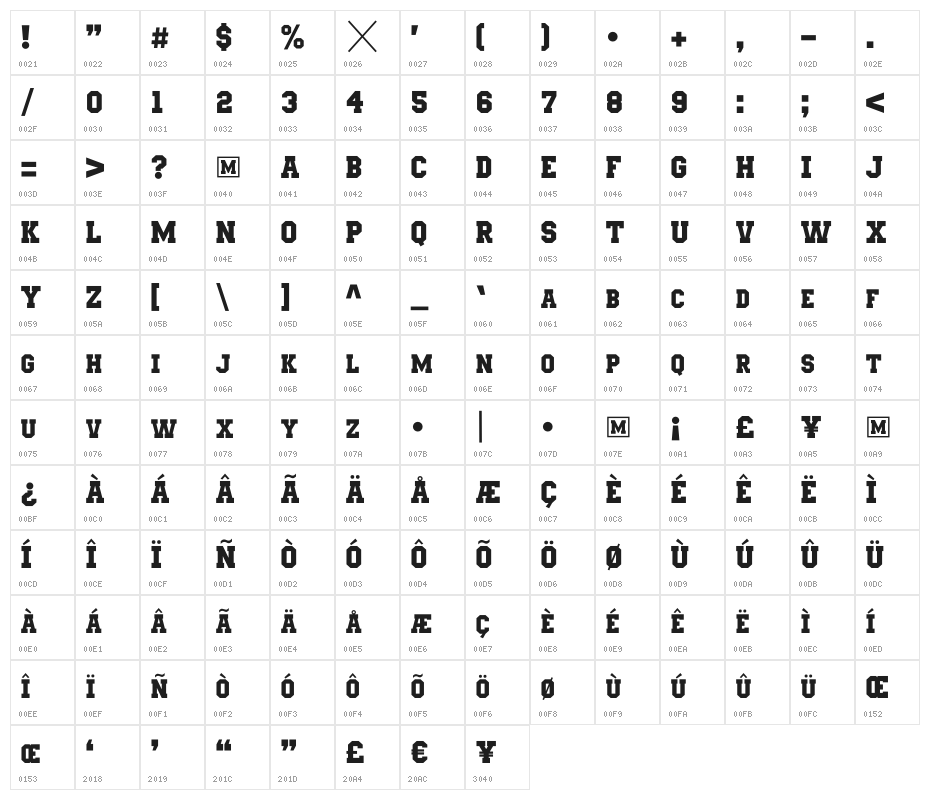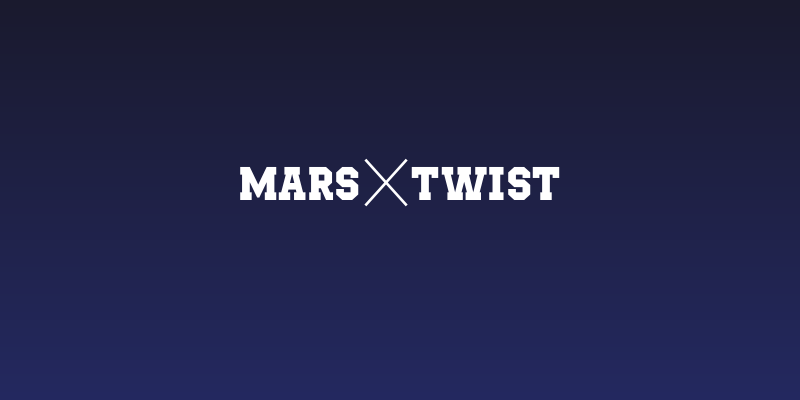
Mars&Twist Font
| Gesamtstil | Vintage |
| Vorgeschlagene Projekte | Ideal for sports branding, posters, headlines, and any project needing a bold, impactful typeface. |